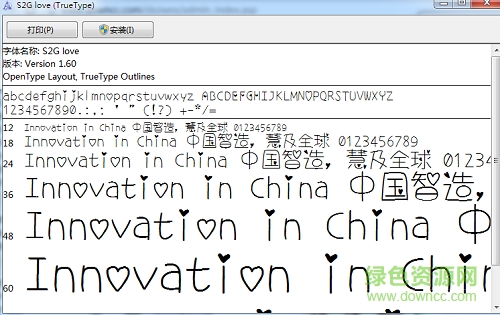
可愛的心形中文字體s2g love
s2g love字體又稱可愛的心形中文字體s2g love,顧名思義是一款非常適合女生的電腦字體,可以讓你打出來的字每一個都可愛無比,喜歡的朋友歡迎下載!
s2g love字體簡介
s2g love字體是一款可愛的心形中文字體,它可以將用戶打出的文字呈現(xiàn)出帶“心”的一年字體樣式,非常的Q萌可愛,非常具備藝術(shù)感,適合永磊進(jìn)行各種藝術(shù)創(chuàng)作!